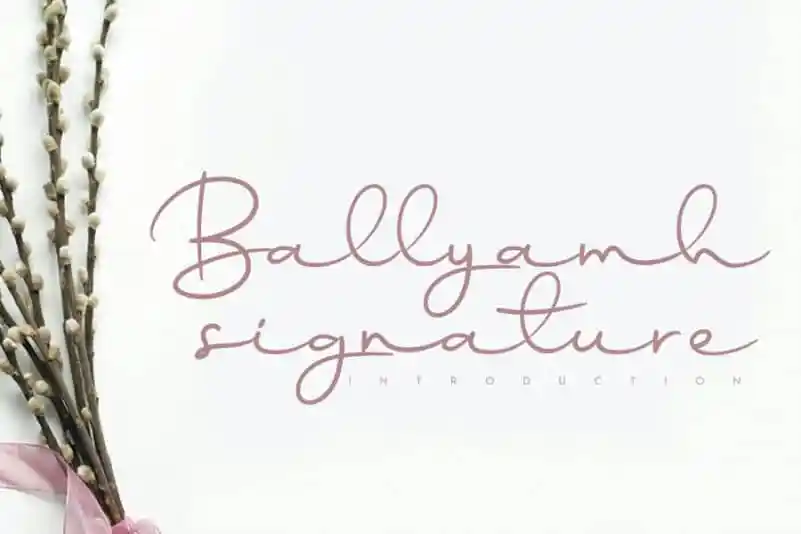
Ballyamh Handwritten Font
A Ballyamh Handwritten Font é uma preciosidade criada para ser uma escolha favorita entre os designers. Ela transmite uma elegância clássica do calligráfico, mas também apresenta um ar contemporâneo e moderno que torna esta fonte única e invigorante. Este design cuidadosamente elaborado preserva as influências de estilo da escrita a mão enquanto a mantém fresca e atualizada para os projetos de hoje. Se apaixonar por Ballyamh Handwritten Font é o seu objetivo, prepare-se para subir ao ápice de sua habilidade com esta fonte criativa.